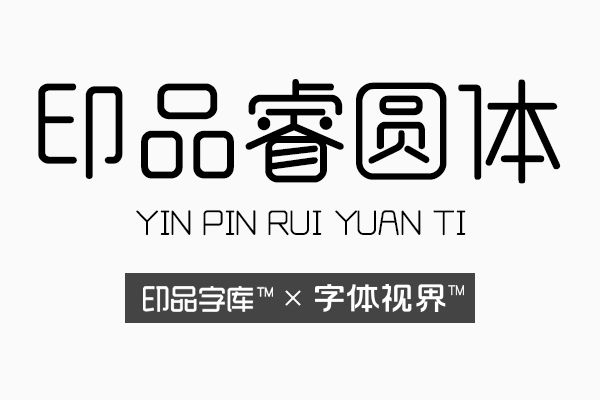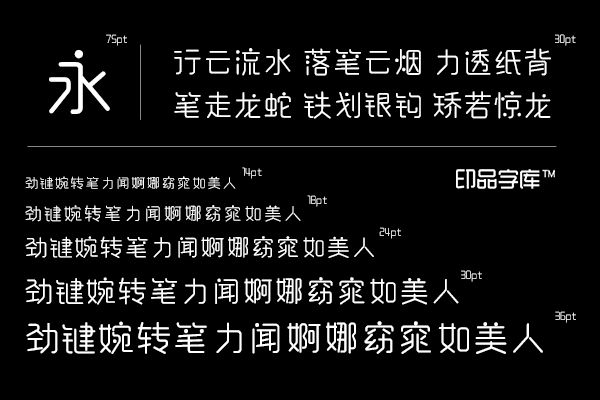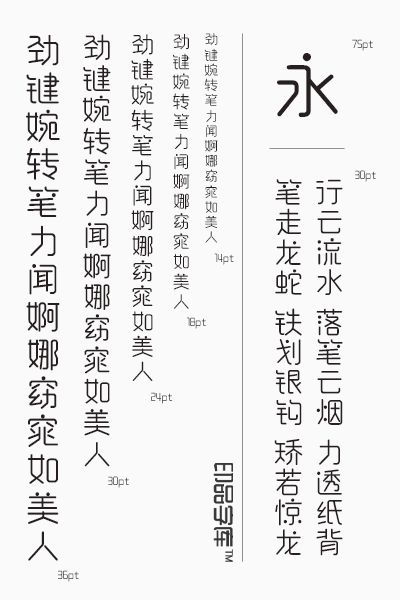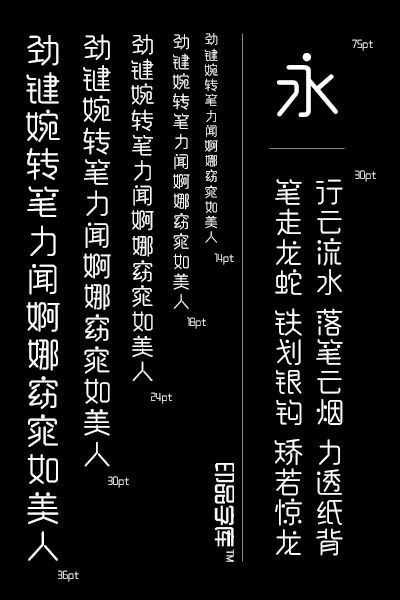
灵动带来精彩生活。舞蹈是有灵性的,当那曼妙的身躯在舞台上跳跃,那种鲜明的动感和无与伦比的跳跃产生的灵动,让人应接不暇。生活中不缺乏字正腔圆的人,缺的是那些能够带给人思考,激发人激情的领袖。现在的年轻人更喜欢,舞动自己,感受着肉体在空中跳动的感觉。有的时候恰似一份灵动,而正是这份灵动带给年轻人无限的遐想。
生活不需要过多的死板,也不需要过多的原则,不拘束不犀利,更多的是在生活沉淀之后,留下了对生的一种重新认知,是对美得一种从新审视。印品睿圆体,摒弃了传统的犀利和柔和,采用了庄重和品质的主题手法。最终展现一种鲜活灵动的视觉美感。
印品睿圆体字体,跳跃在字里行间的精灵。
这款字体,保留了拐角的弧形和圆的特性,同时,在文字的中间加入了圆点的元素。同时,从文字的笔画的走势和粗细进行精心的布局,对下笔的轻重进行把握,从而形成了一个个灵动跳跃的符号,在字体间进行跳动。这种美感,还带有时尚的元素。印品睿圆体字体一款高质量印刷、创意字体,带来生活的感悟。